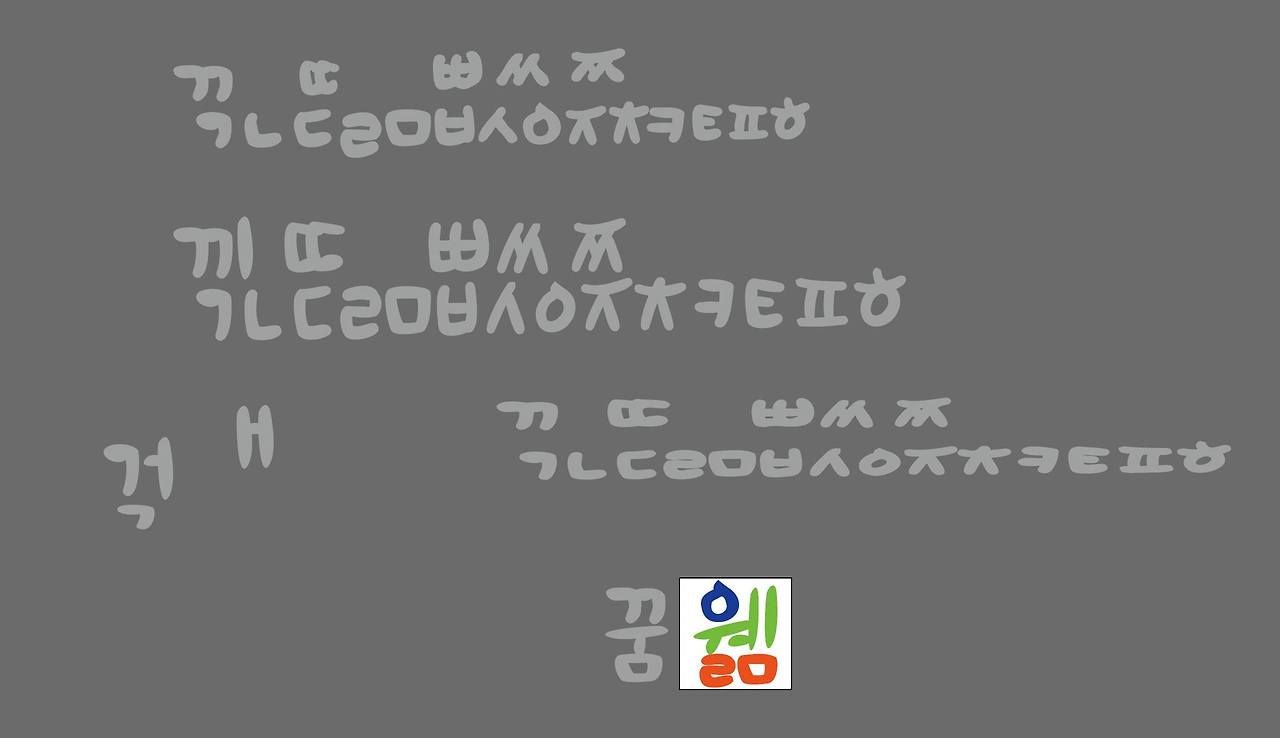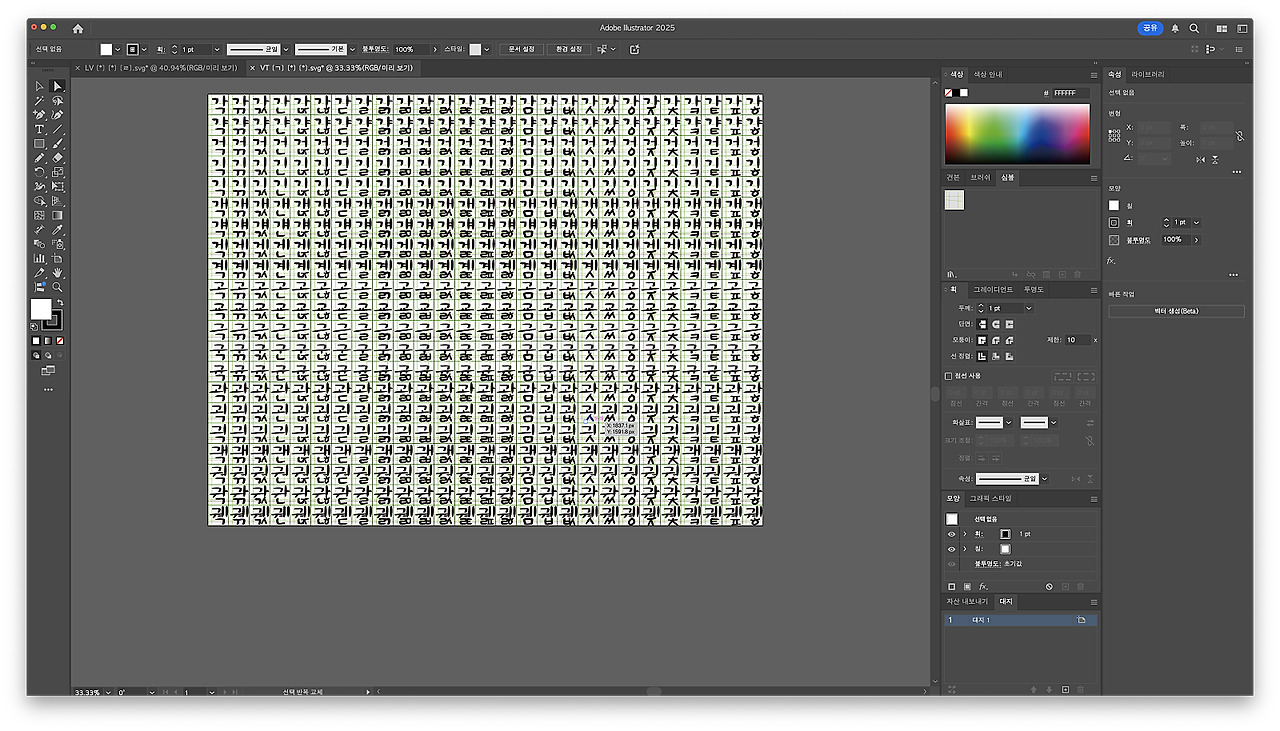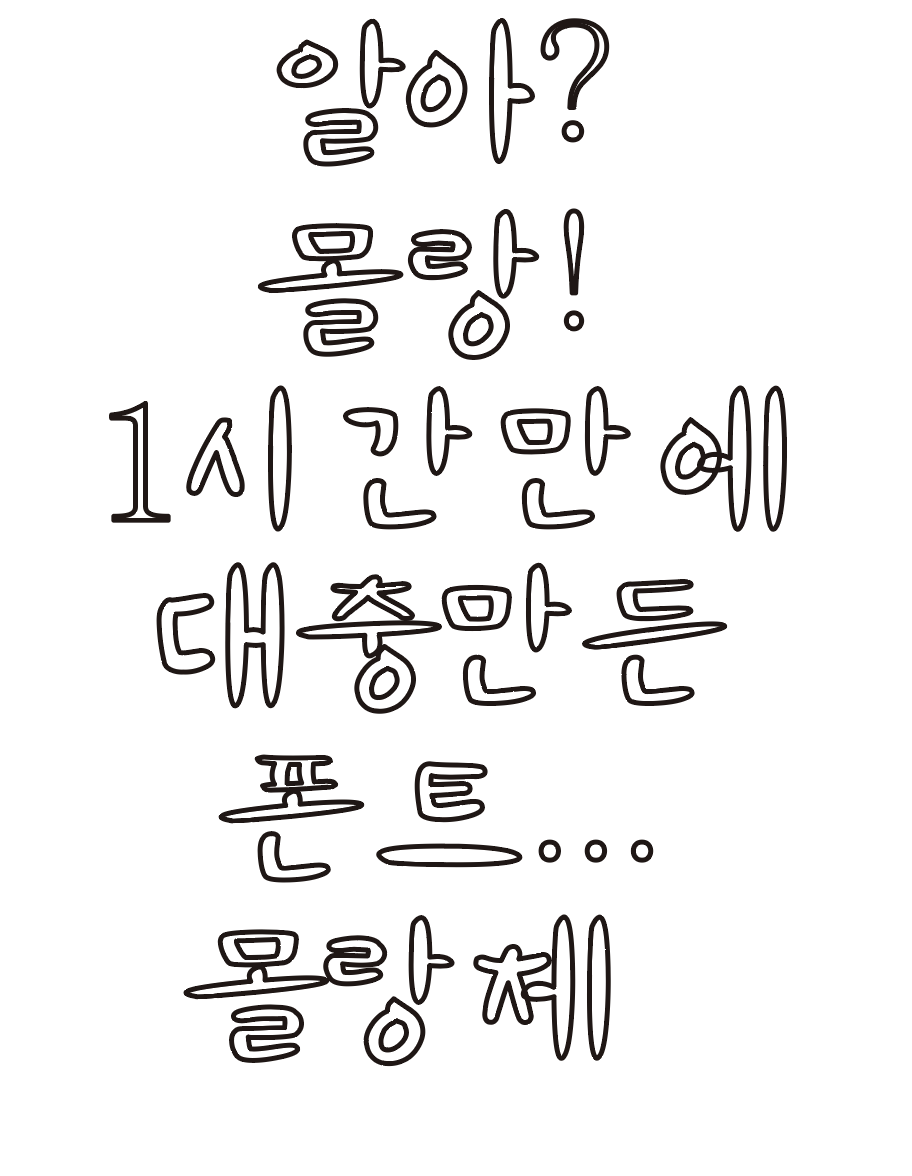
만화효과음 폰트 만들면서
초성조합을 이용한 종성 만들기
사실 몇가지 조합만 가지고 폰트는 만들어집니다. 만화효과음 같은 폰트 샘플이 필요해서 잠깐 만들어봤습니다. 이전에 오라오라체 같은 만화효과음 폰트를 직결식으로 만들었는데 이번에는 완성형폰트로 제작했습니다. 말랑체 라고 마시멜로 같은 느낌으로 글자를 디자인했습니다.
새로 템플릿 구조를 바꾸고 작업하면서 없는 것에서 부터 시작한 글자는 얼마나 걸릴까? 하고 1시간 전에 작업해서 완성을 했습니다. 직결식 방식으로 만들게 초성조합만을 가지고 종성을 만들었습니다. 시간이 절약되고 만화용효과음용으로 만든 샘플이라 앞으로 자막같은데도 사용해보려고 합니다.
가이드를 바꾸고 한 눈에 보면서 작업하는 것이 편하고 좋은데 일러스트레이터가 10000 픽셀 이상의 사이즈를 안열고 줄여버리는 일이 생겨서 그건 어도비가 막아놓은 것을 확인했습니다.
다른 프로그램은 이상없이 열리는데 SVG를 만든 어도비가 막고 있어서 그 부분에 대한 고민과 inkscape, fontforge 를 자동화해서 배열하는 자동처리를 하다가 일단 멈췄습니다.
아마 손글씨가 아닌 만화용 서체 작업할 때 필요해서 일단 뒤로 미뤘습니다.
사실 폰트를 만들 때 컴포넌트를 만들어서 글씨가 어떤 모양에 따라 다 다른 초성을 만들어 넣게됩니다. 예를 들어 ㅔㅣ 같은 경우 초성의 모양이 달라지죠... 저희가 만든 폰트 생성기는 바로 폰트편집기에서 부분 수정이 모두 가능하도록 작업을 해놨습니다.
만화쪽에도 각도에 따라 다른 글자의 형태가 나오게 하는 것이 필요한데 퍼스펙티브 시점에 맞춰 효과음이 날라가는 듯한 이펙트를 만들 수 있는 편집기에 집중하는 중입니다.